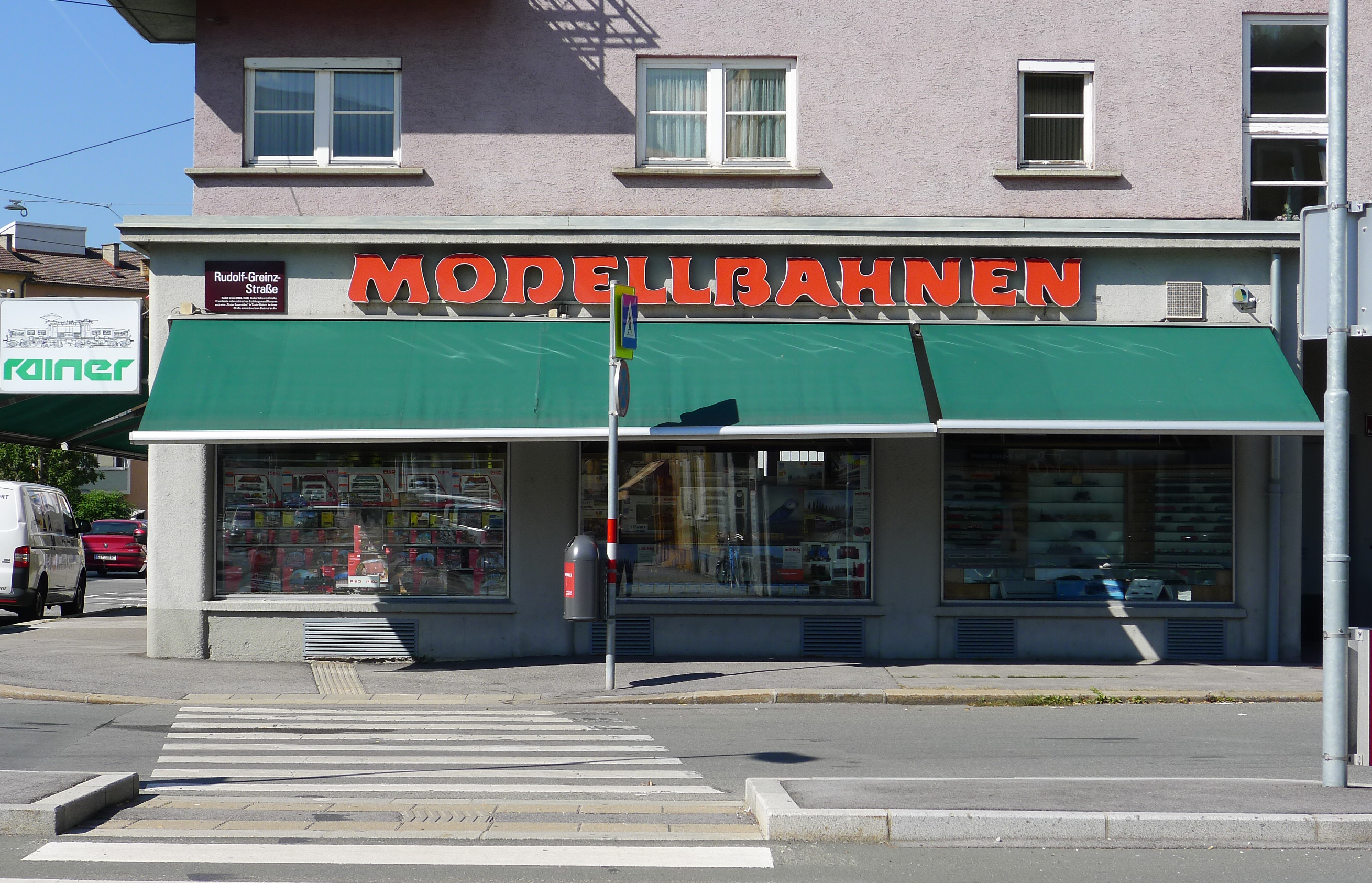
Modellbau Amras
Eine Schrift die wohl extra für diesen Fall angefertigt wurde. Typografisch herrlich ...na ja...patschert – man beachte vor allem das O und das A – aber dennoch charmant, vor allem zusammen mit der grünen Markise. Ein bisschen mehr Platz oben und unten hätte nicht geschadet.